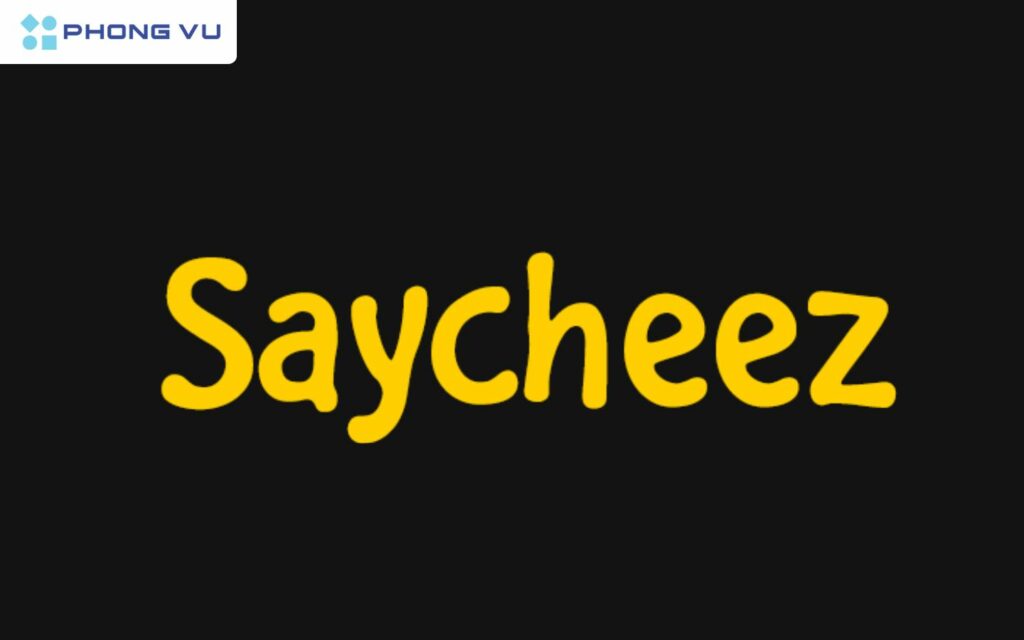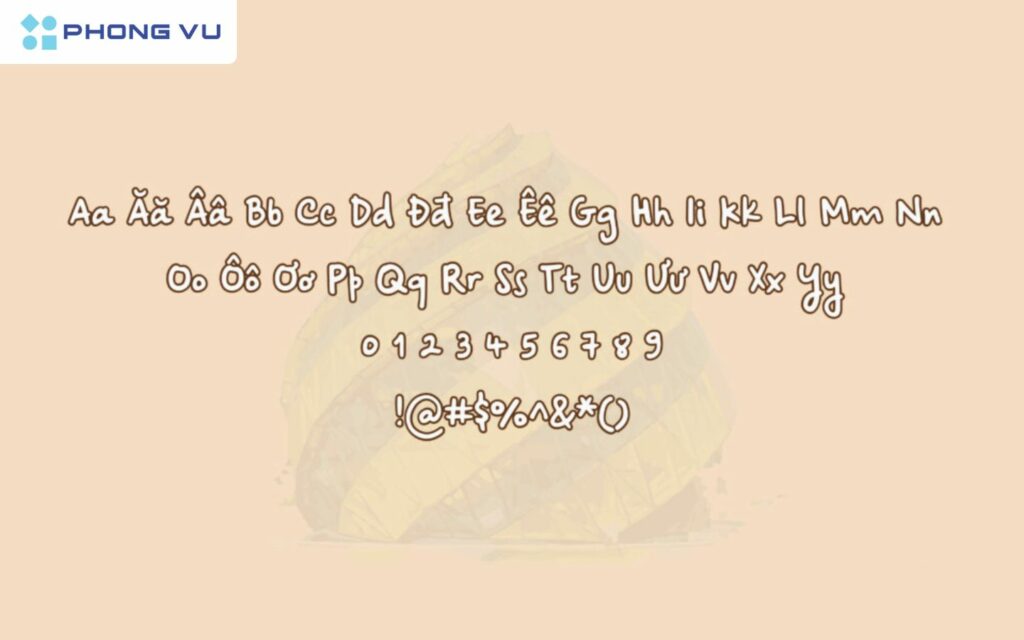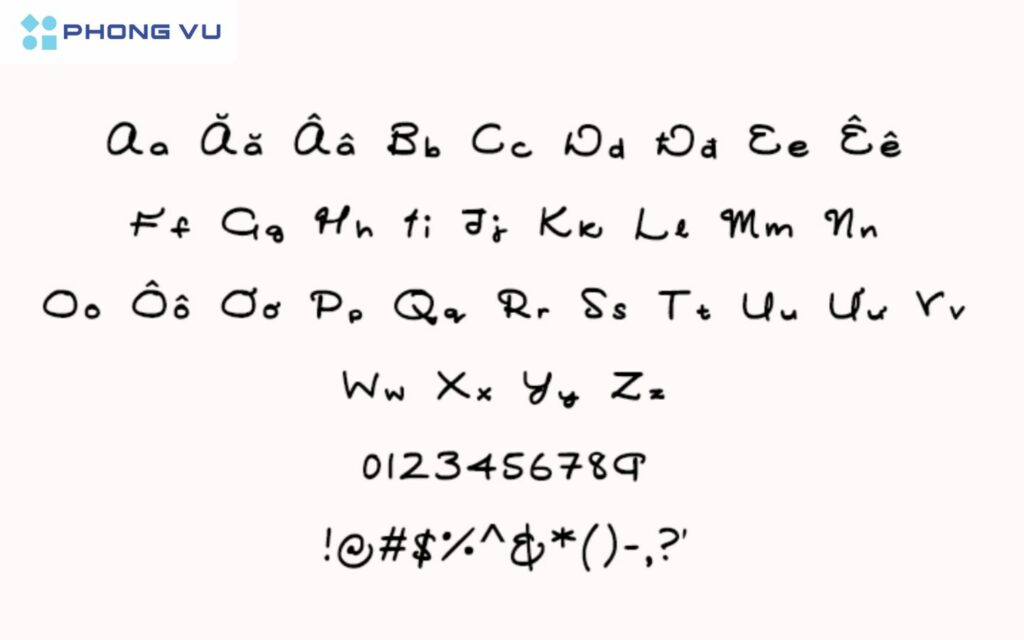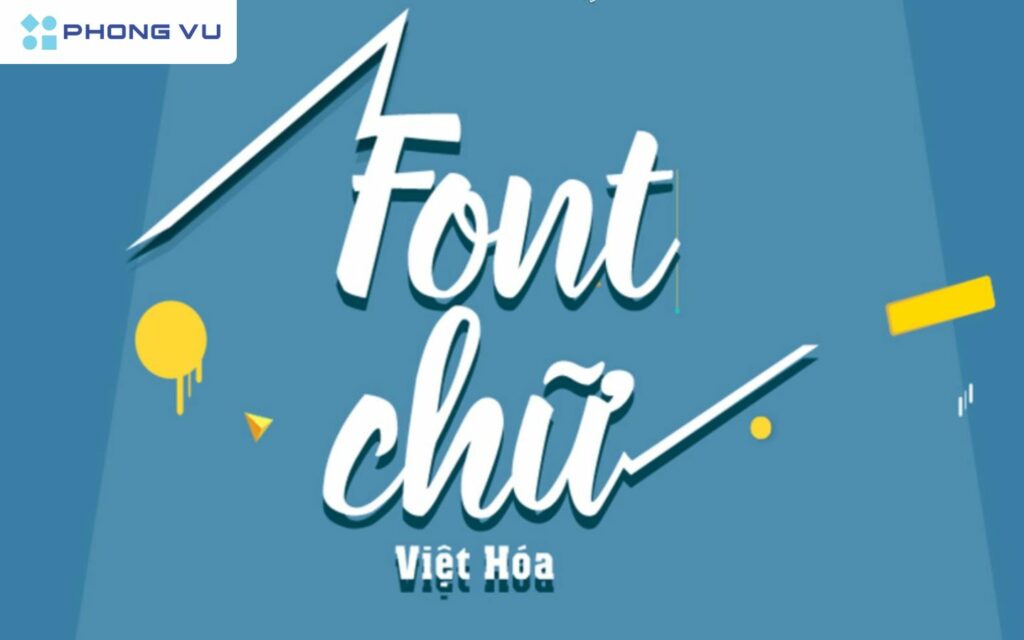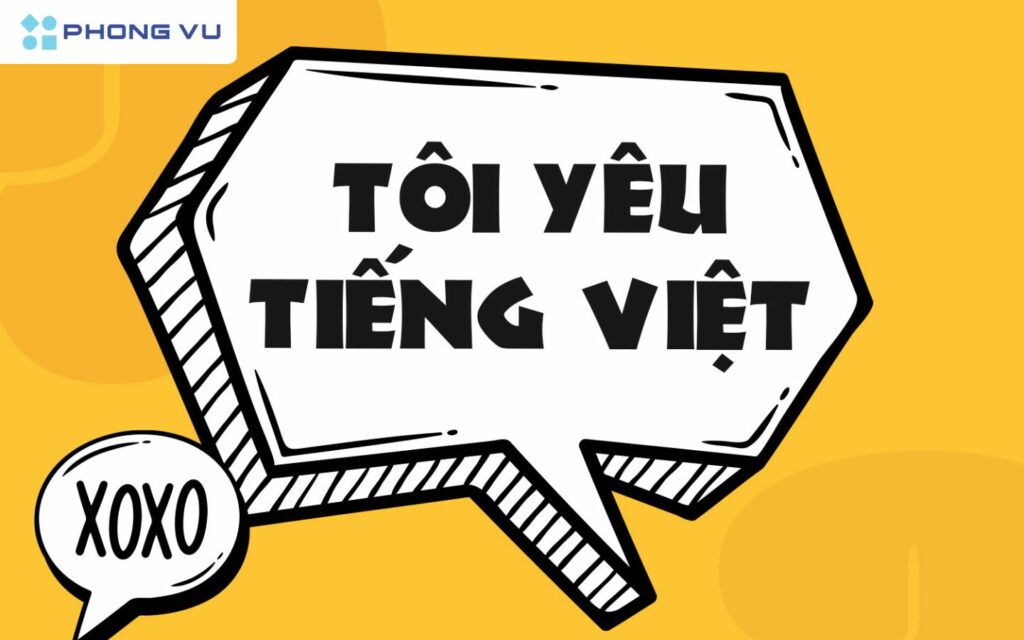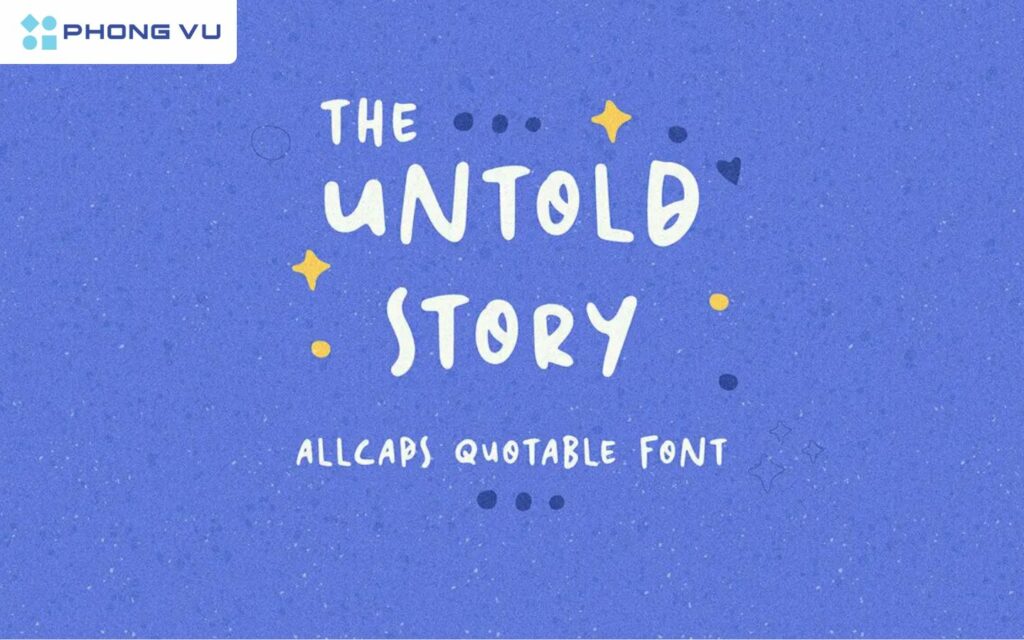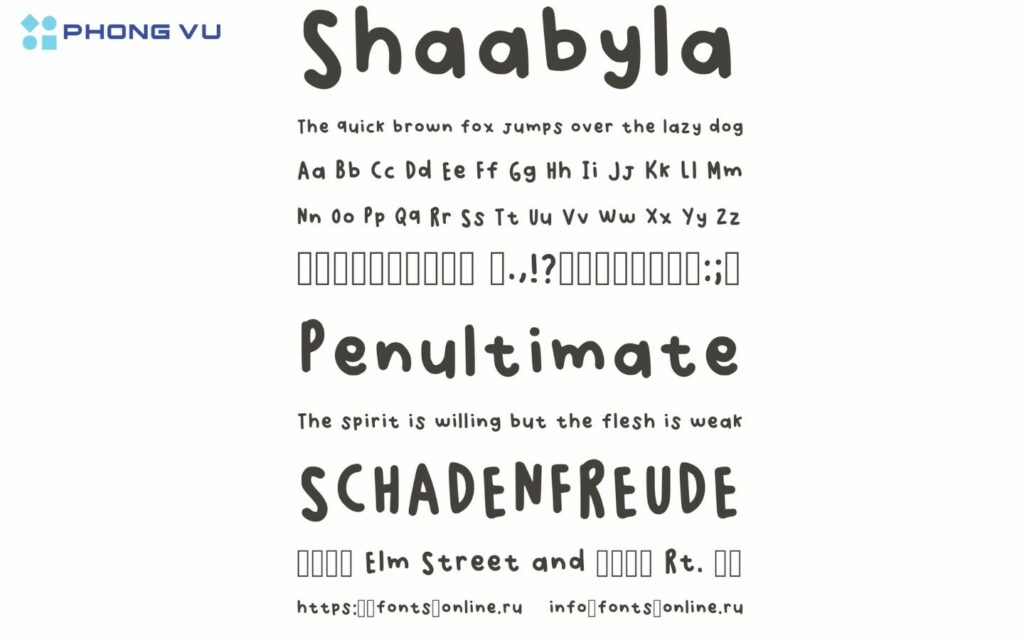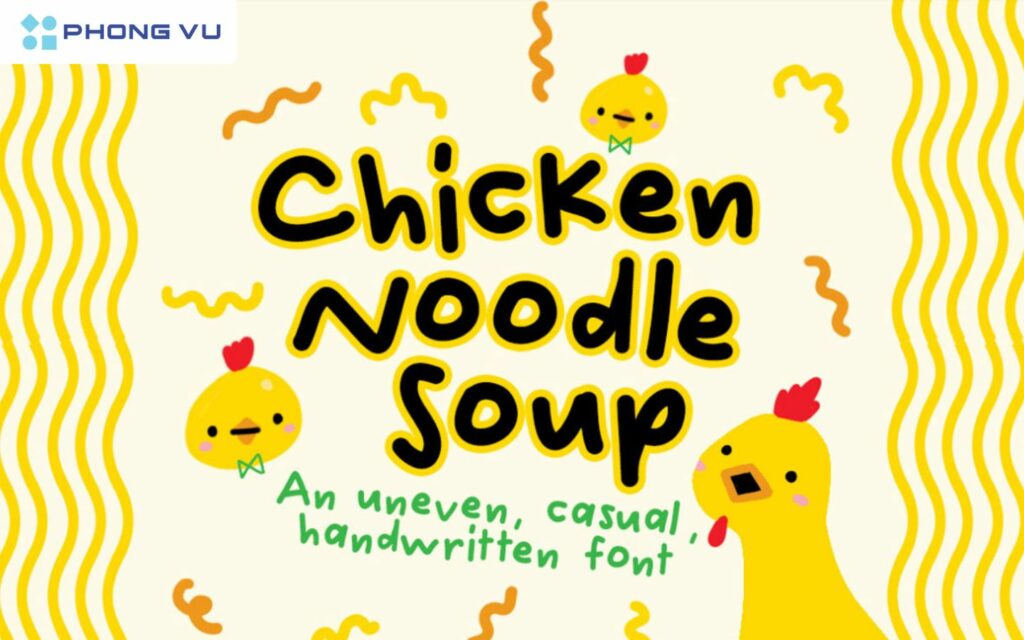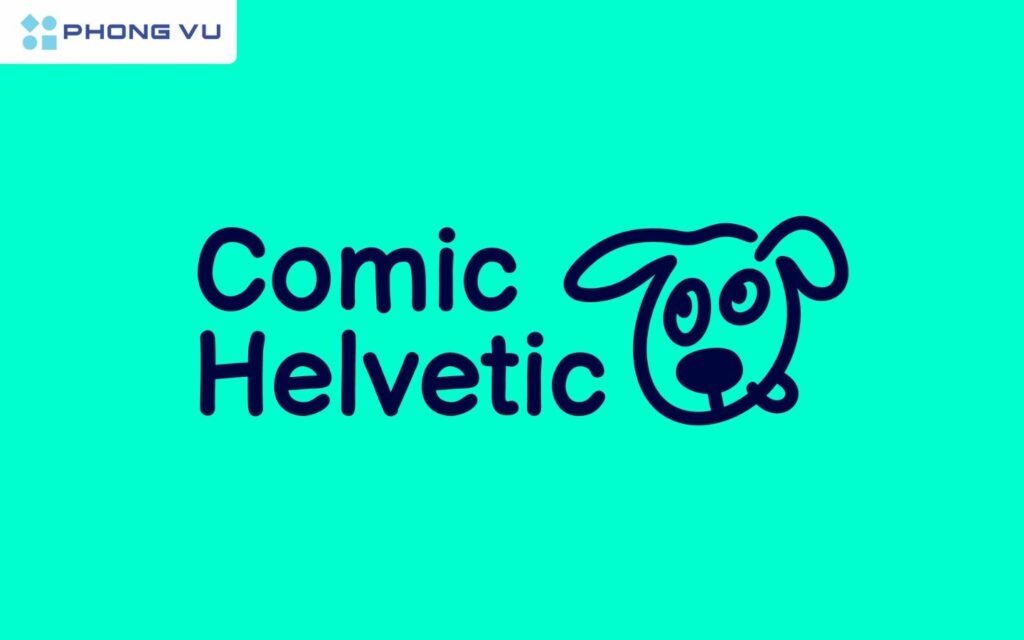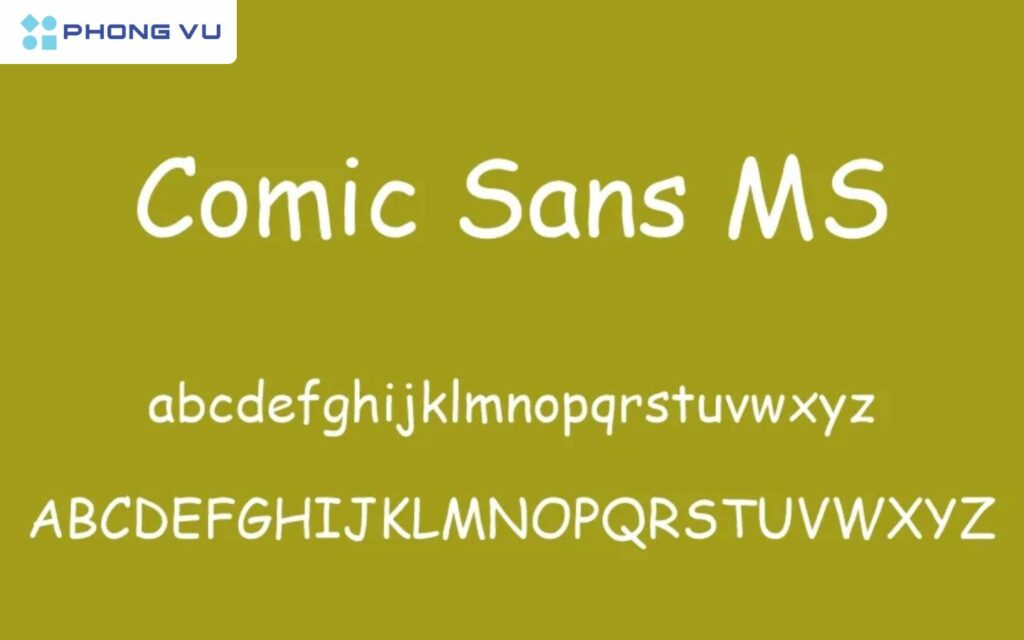
Top 9 Font chữ Việt hóa để edit Vlog đẹp, độc đáo nhất 2025
Font chữ đẹp và độc đáo là yếu tố quan trọng giúp video Vlog trở nên chuyên nghiệp và cuốn hút hơn. Nếu bạn đang tìm kiếm những font chữ Việt hóa để edit Vlog đẹp và ấn tượng nhất trong năm 2025, bài viết này sẽ gợi ý cho bạn 9 lựa chọn hàng đầu. Từ phong cách hiện đại, tối giản đến nghệ thuật và cá tính, những font chữ này sẽ giúp bạn tạo điểm nhấn và truyền tải nội dung hiệu quả hơn. Cùng Phong Vũ Tech News khám phá ngay!
Font chữ Việt hóa là gì?
Font chữ Việt hóa là các font chữ được thiết kế hoặc điều chỉnh để hỗ trợ đầy đủ các ký tự trong bảng chữ cái tiếng Việt
Font chữ Việt hóa là những phông chữ đã được chỉnh sửa và bổ sung đầy đủ dấu, ký tự tiếng Việt để hiển thị chính xác trên các thiết bị và phần mềm thiết kế. Nhiều font chữ nước ngoài khi sử dụng trong tiếng Việt có thể bị lỗi dấu hoặc thiếu ký tự đặc trưng như “ă, â, ê, ô, ơ, ư, đ”. Vì vậy, quá trình Việt hóa giúp font chữ tương thích hoàn toàn với tiếng Việt, mang lại trải nghiệm tốt hơn khi thiết kế đồ họa, chỉnh sửa video, làm Vlog hoặc soạn thảo văn bản.
Font chữ Việt hóa có đặc điểm gì?
Font chữ Việt hóa đảm bảo hiển thị chính xác và thẩm mỹ
Font chữ Việt hóa được tạo ra nhằm đảm bảo tính thẩm mỹ và khả năng hiển thị tốt nhất khi sử dụng trong thiết kế hoặc chỉnh sửa nội dung bằng tiếng Việt. Dưới đây là một số đặc điểm nổi bật của font chữ Việt hóa:
• Hỗ trợ đầy đủ dấu và ký tự tiếng Việt: Các font chữ Việt hóa được bổ sung các ký tự đặc trưng như “ă, â, ê, ô, ơ, ư, đ” cùng dấu thanh để đảm bảo hiển thị chính xác.
• Giữ nguyên phong cách thiết kế gốc: Khi Việt hóa, font chữ vẫn giữ nguyên nét đặc trưng về kiểu dáng, giúp người dùng có nhiều sự lựa chọn phù hợp với phong cách thiết kế.
• Tương thích với nhiều phần mềm: Font chữ Việt hóa có thể sử dụng trên Photoshop, Premiere, Canva, CapCut, After Effects và nhiều công cụ chỉnh sửa Vlog, thiết kế đồ họa khác.
• Đa dạng phong cách: Có nhiều kiểu font Việt hóa từ đơn giản, tối giản đến nghệ thuật, thư pháp hoặc mang phong cách retro, giúp Vlog của bạn trở nên độc đáo hơn.
• Tính chuyên nghiệp: Việc sử dụng font Việt hóa thể hiện sự tôn trọng ngôn ngữ và văn hóa Việt Nam. Từ đó giúp các sản phẩm thiết kế trở nên chuyên nghiệp và chỉn chu hơn.
Nhờ những đặc điểm trên, font chữ Việt hóa là lựa chọn không thể thiếu cho những ai muốn tạo nội dung video chuyên nghiệp và thu hút hơn.
Top 9 Font chữ Việt hóa đẹp nhất để edit Vlog
Việc lựa chọn font chữ phù hợp sẽ giúp Vlog của bạn trở nên chuyên nghiệp, thu hút và thể hiện được phong cách cá nhân. Dưới đây là danh sách 9 font chữ Việt hóa đẹp nhất, phù hợp cho nhiều phong cách chỉnh sửa Vlog khác nhau, từ hiện đại, tối giản đến nghệ thuật và cá tính. Cùng khám phá ngay để tìm ra font chữ ưng ý nhất cho video của bạn!
Font: The Untold Story
The Untold Story là một kiểu chữ đầy tính nghệ thuật, mang phong cách vintage với những đường nét mềm mại nhưng không kém phần cá tính. Font này thường được sử dụng trong các thiết kế mang hơi hướng hoài cổ, từ bìa sách, poster phim đến logo thương hiệu. Đặc điểm nổi bật của The Untold Story là sự kết hợp hài hòa giữa các nét cong duyên dáng và những khoảng hở hợp lý, giúp từng ký tự trở nên dễ đọc và thu hút. Với vẻ đẹp cổ điển nhưng không lỗi thời, font này mang đến cảm giác bí ẩn và quyến rũ đúng như cái tên của nó.
Một font chữ mang đậm tính kể chuyện
Font: Shaabyla
Shaabyla là một kiểu chữ mang đậm phong cách thủ công với những đường nét uốn lượn tự nhiên, phù hợp cho các thiết kế cần sự mềm mại, bay bổng. Font này thường được sử dụng trong các dự án sáng tạo như typography art, thiệp chúc mừng hay bao bì sản phẩm handmade. Shaabyla có sự biến tấu độc đáo giữa nét dày và nét mỏng, tạo nên cảm giác uyển chuyển nhưng vẫn đảm bảo tính dễ đọc. Với sự kết hợp giữa sự phóng khoáng và thanh lịch, Shaabyla là lựa chọn lý tưởng cho những ai muốn tạo điểm nhấn đặc biệt trong thiết kế.
Font chữ script thanh lịch
Font: SVN – Chicken Noodle Soup
SVN – Chicken Noodle Soup là một font chữ vui nhộn, đáng yêu với những nét cong tròn trịa gợi nhớ đến phong cách viết tay trẻ trung. Font này phù hợp với các thiết kế dành cho trẻ em, thực phẩm, hoặc các sản phẩm có phong cách thân thiện, gần gũi. Điểm đặc biệt của Chicken Noodle Soup là cách tạo hình chữ mềm mại nhưng vẫn rõ ràng, giúp thiết kế trở nên sinh động mà không mất đi sự chuyên nghiệp. Nếu bạn đang tìm kiếm một kiểu chữ vừa ngộ nghĩnh, vừa dễ đọc, font này chắc chắn sẽ là sự lựa chọn không thể bỏ qua.
Font chữ vui tươi và ngộ nghĩnh
Font: Comic Helvetic Heavy
Comic Helvetic Heavy là sự kết hợp hoàn hảo giữa phong cách Comic Sans và Helvetica, tạo nên một font chữ vui nhộn nhưng vẫn rõ ràng, dễ đọc. Với độ dày nổi bật, font này rất thích hợp để làm tiêu đề hoặc phần nhấn mạnh trong Vlog hài hước, review sản phẩm hoặc nội dung sáng tạo. Comic Helvetic Heavy giúp tăng thêm sự chuyên nghiệp mà không làm mất đi sự vui nhộn của video.
Font chữ mềm mại và duyên dáng
Tổng kết